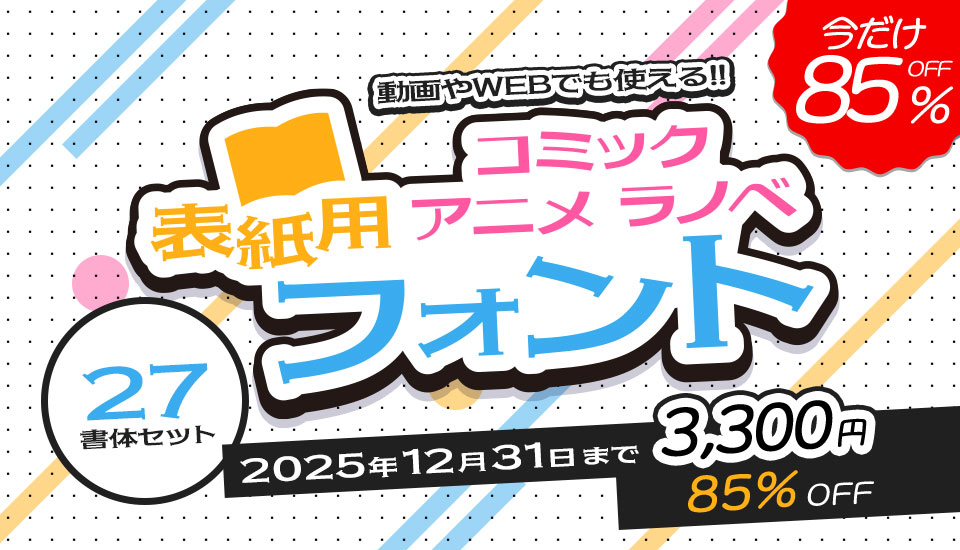
AFSアニメコミックラノベ表紙用フォント
AFSアニメコミックラノベ表紙用フォント 27書体セット
AFSアニメコミックラノベ表紙用フォント 27書体セット 収録書体見本
AFSアニメコミックラノベ表紙用フォント
AFSアニメコミックラノベ表紙用フォントは、メイリオの日本語パートのデザイナーとして知られる鈴木竹治氏によるデザイン書体の中からアニメ・コミック表紙、動画に最適なフォントを厳選。基本書体は、おぼろ、オリーブ、クロス、セリフゴシック、フローラ、マカロン、めいげつ、リモーネ、雲水の10書体。収録文字セットはJIS第一水準と第二水準の一部の漢字を収録。
AFSアニメコミックラノベ表紙用フォント 27書体セット セット内容
1. AFSコミックセリフゴシック 04E / 90E
AFSコミックセリフゴシック 04E / 90E サンプル AFSコミックセリフゴシック 04E / 90E 文字見本 AFSコミックセリフゴシック 04E / 90E 組み見本
JIS2004字形とJIS90字形の2書体をご用意しています。
AFSコミックセリフゴシック 04E
AFSコミックセリフゴシック 04E 字形見本
AFSコミックセリフゴシック 90E
AFSコミックセリフゴシック 90E 字形見本
2. AFSコミッククロス 04E / 90E
AFSコミッククロス 04E / 90E サンプル AFSコミッククロス 04E / 90E 文字見本 AFSコミッククロス 04E / 90E 組み見本
JIS2004字形とJIS90字形の2書体をご用意しています。
AFSコミッククロス 04E
AFSコミッククロス 04E 字形見本
AFSコミッククロス 90E
AFSコミッククロス 90E 字形見本
3. AFSコミッククロス 04U / 90U
AFSコミッククロス 04U / 90U サンプル AFSコミッククロス 04U / 90U 文字見本 aFSAFSコミッククロス 04U / 90U 組み見本
JIS2004字形とJIS90字形の2書体をご用意しています。
コミッククロス 04U
AFSコミッククロス 04U見本
コミッククロス 90U
AFSコミッククロス 90U見本
4. AFSコミックマカロン EL1
AFSコミックマカロン EL1 サンプル AFSコミックマカロン EL1 文字見本 AFSコミックマカロン EL1 組み見本
5. AFSコミックマカロン EL2
AFSコミックマカロン EL2 サンプル AFSコミックマカロン EL2 文字見本 AFSコミックマカロン EL2 組み見本
6. AFSコミックマカロン B1
AFSコミックマカロン B1 サンプル AFSコミックマカロン B1 文字見本 AFSコミックマカロン B1 組み見本
7. AFSコミックマカロン B2
AFSコミックマカロン B2 サンプル AFSコミックマカロン B2 文字見本 AFSコミックマカロン B2 組み見本
8. AFSコミックテンドゥ 04EL / 90EL
AFSコミックテンドゥ 04EL / 90EL サンプル AFSコミックテンドゥ 04EL / 90EL 文字見本 AFSコミックテンドゥ 04EL / 90EL 組み見本
JIS2004字形とJIS90字形の2書体をご用意しています。
AFSコミックテンドゥ 04EL
AFSコミックテンドゥ 04EL 字形見本
AFSコミックテンドゥ 90EL
AFSコミックテンドゥ 90EL 字形見本
9. AFSコミックテンドゥ 04R / 90R
AFSコミックテンドゥ 04R / 90R サンプル AFSコミックテンドゥ 04R / 90R 文字見本 AFSコミックテンドゥ 04R / 90R 組み見本
JIS2004字形とJIS90字形の2書体をご用意しています。
AFSコミックテンドゥ 04R
AFSコミックテンドゥ 04R 字形見本
AFSコミックテンドゥ 90R
AFSコミックテンドゥ 90R 字形見本
10. AFSコミックリモーネ 04R / 90R
AFSコミックリモーネ 04R / 90R サンプル AFSコミックリモーネ 04R / 90R 文字見本 AFSコミックリモーネ 04R / 90R 組み見本
JIS2004字形とJIS90字形の2書体をご用意しています。
AFSコミックリモーネ 04R
AFSコミックリモーネ 04R 字形見本
AFSコミックリモーネ 90R
AFSコミックリモーネ 90R 字形見本
11. AFSコミックリモーネ 04B / 90B
AFSコミックリモーネ 04B / 90B サンプル AFSコミックリモーネ 04B / 90B 文字見本 AFSコミックリモーネ 04B / 90B 組み見本
JIS2004字形とJIS90字形の2書体をご用意しています。
AFSコミックリモーネ 04B
AFSコミックリモーネ 04B 字形見本
AFSコミックリモーネ 90B
AFSコミックリモーネ 90B 字形見本
12. AFSコミックフローラ 04U / 90U
AFSコミックフローラ 04U / 90U サンプル AFSコミックフローラ 04U / 90U 文字見本 AFSコミックフローラ 04U / 90U 組み見本
JIS2004字形とJIS90字形の2書体をご用意しています。
AFSコミックフローラ 04U
AFSコミックフローラ 04U 字形見本
AFSコミックフローラ 90U
AFSコミックフローラ 90U 字形見本
13. AFSコミックオリーブ 04EL / 90EL
AFSコミックオリーブ 04EL / 90EL サンプル AFSコミックオリーブ 04EL / 90EL 文字見本 AFSコミックオリーブ 04EL / 90EL 組み見本
JIS2004字形とJIS90字形の2書体をご用意しています。
AFSコミックオリーブ 04EL
AFSコミックオリーブ 04EL 字形見本
AFSコミックオリーブ 90EL
AFSコミックオリーブ 90EL 字形見本
14. AFSコミックおぼろ1
AFSコミックおぼろ1 サンプル AFSコミックおぼろ1 文字見本 AFSコミックおぼろ1 組み見本
15. AFSコミックおぼろ2
AFSコミックおぼろ2 サンプル AFSコミックおぼろ2 文字見本 AFSコミックおぼろ2 組み見本
16. AFSコミックれいこう
AFSコミックれいこう サンプル AFSコミックれいこう 文字見本 AFSコミックれいこう 組み見本
17. AFSコミック雲水
AFSコミック雲水 サンプル AFSコミック雲水 文字見本 AFSコミック雲水 組み見本
18. AFSコミックめいげつ
AFSコミックめいげつ サンプル AFSコミックめいげつ 文字見本 AFSコミックめいげつ 組み見本